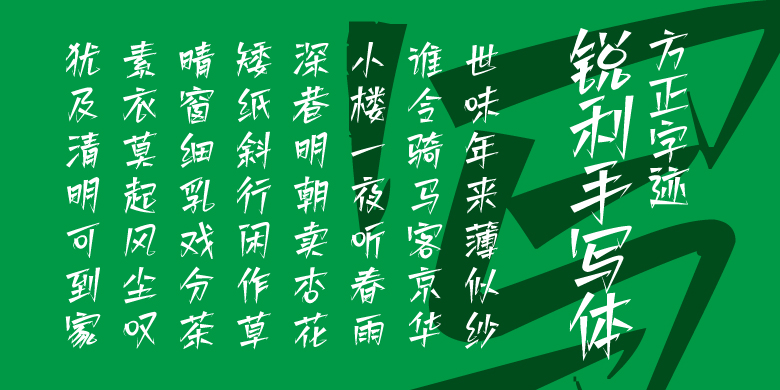
方正字汇-锐利手写体
李路生
创意书写
锐利手写体,前后对该字体多次打磨,力求精益。该字体具有以下特点: 1.独特性与创新性,该字体以其锋利的笔触和带有菱角的字形设计,形成了自己独有的风格。使得该字体在字库市场中具有很高的辨识度和吸引力。 2.传达力与情感表达,该字体在情感表达上,可以传达出一种坚定、果断、有力的情感。并在传递信息时更具有感染力和说服力。3.易于识别与记忆,该字独特的风格使得它在众多字体中易于被识别和记忆,这种特性使得该字体在字库市场中具有更高的用户粘性和重复使用率。